Die schönsten handschriftlichen Schriftarten zum Gestalten und Beschriften von Bildern in der App
Handschriftliche Schriftarten verleihen eine persönliche Note und eignen sich für viele Anlässe. Sie helfen, die eigene Identität oder eine besondere Stimmung auszudrücken. Besonders für Einladungen, Grußkarten, Branding, oder kunstvolle Designs sind Handschriften eine gute Wahl.
Handschrift-Schriftarten, die du kennen solltest
Fonts sind digitale Schriftarten und bestimmen das Erscheinungsbild von Buchstaben, Zahlen und Symbolen. Ein handschriftlicher Font vermittelt eine persönliche und vertraute Note. PhotoDirector bietet eine große Auswahl an schönen Handschrift-Schriftarten, die du direkt in der App nutzen kannst, um deine Bilder kreativ zu beschriften und zu gestalten. Doch bei der Vielzahl an Optionen fällt die Wahl oft schwer. Im Folgenden stellen wir dir zehn hochwertige Handschrift-Schriftarten vor.
- Satisfy
- Petit Formal Script
- Just Another Hand
- Nothing You Could Do
- Patrick Hand SC
- Oooh Baby
- Just Me Again Down Here
- Trade Winds
- Haedus
- Caveat
1. Satisfy
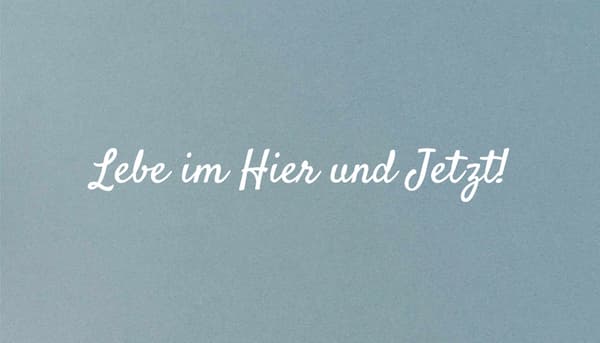
"Satisfy" ist eine beliebte Handschrift-Schriftart, die Eleganz mit einer persönlichen Note verbindet. Dank ihrer gut lesbaren Buchstaben eignet sie sich perfekt für Einladungen, Grüße und kreative Designs.
2. Petit Formal Script
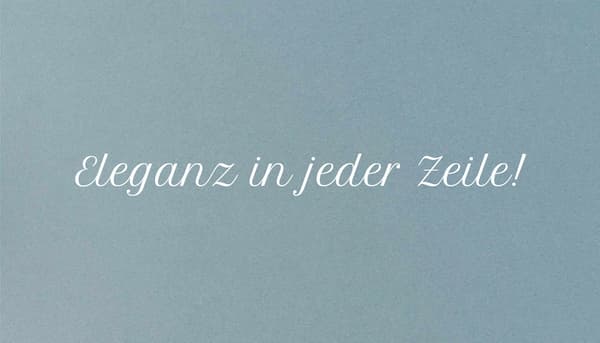
"Petit Formal Script" vereint die Eleganz handschriftlicher Linien mit einer klaren, strukturierten Ästhetik. Diese Schriftart ist ideal für klassische Einladungen, luxuriöses Branding und edle Verpackungsdesigns.
3. Just Another Hand
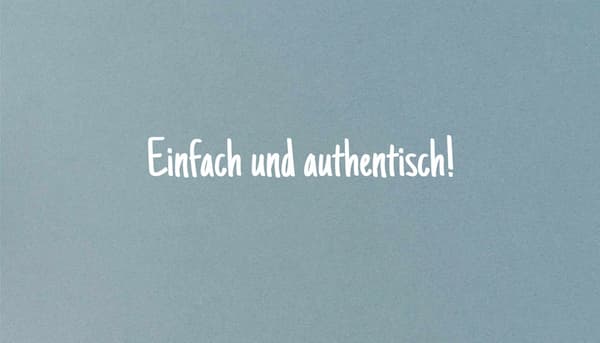
"Just Another Hand" ist eine schmale, mit dem Pinsel gezeichnete Handschrift, die von der Handschrift des Erstellers aus seiner Highschool-Zeit inspiriert wurde. Diese Schriftart wird häufig für Grußkarten, persönliche Briefe und Einladungen verwendet.
4. Nothing You Could Do
"Nothing You Could Do" ist eine natürliche, verspielte Schrift mit einem leicht schrägen Look. Ihre Schönheit liegt in ihrer Unvollkommenheit und Spontaneität. Sie eignet sich besonders für Designs, die Persönlichkeit und Individualität ausstrahlen.
5. Patrick Hand SC
"Patrick Hand SC" ist eine klare, gut lesbare Handschrift-Schriftart in Großbuchstaben. Sie eignet sich ideal für freundliche Anzeigen und Kinderbücher.
6. Oooh Baby
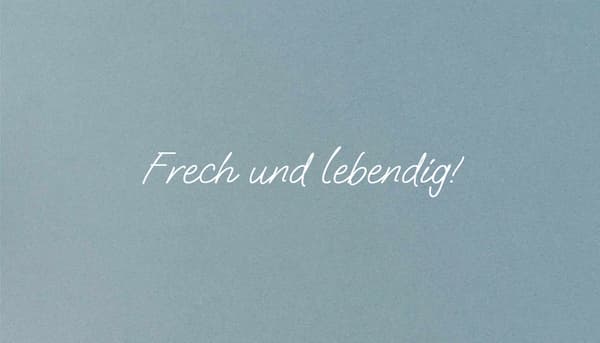
"Oooh Baby" ist eine fröhliche, verspielte Handschrift-Schriftart, die Designs eine lebendige und persönliche Note verleiht. Sie ist hervorragend für Einladungskarten, Produktverpackungen und ungezwungene Designs.
7. Just Me Again Down Here
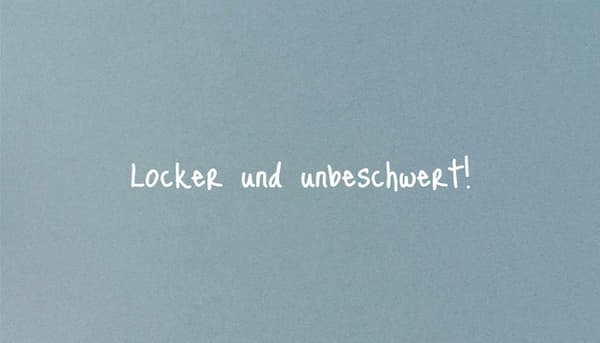
"Just Me Again Down Here" ist eine süße, leicht unordentliche Handschrift-Schriftart mit charmantem Charakter. Sie eignet sich ideal für freundliche Erinnerungen, persönliche Briefe und kreative Anzeigen.
8. Trade Winds
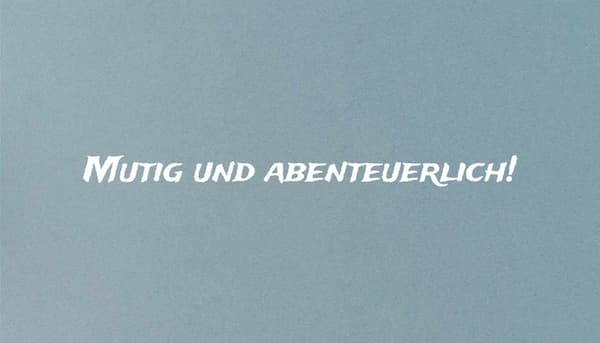
"Trade Winds" ist eine markante Handschrift-Schriftart in Großbuchstaben, die ein Gefühl von Abenteuer und Bewegung vermittelt. Sie eignet sich ideal für Branding, Reiseprojekte und sportliche Designs.
9. Haedus
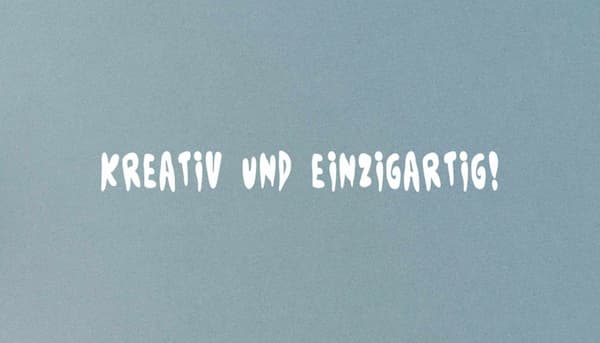
"Haedus" zeichnet sich durch eine kühne, handgemalte Ästhetik aus und verleiht Designs eine düstere, gruselige Atmosphäre. Diese Schriftart eignet sich perfekt für Halloween-Themen und Horror-Designs.
10. Caveat
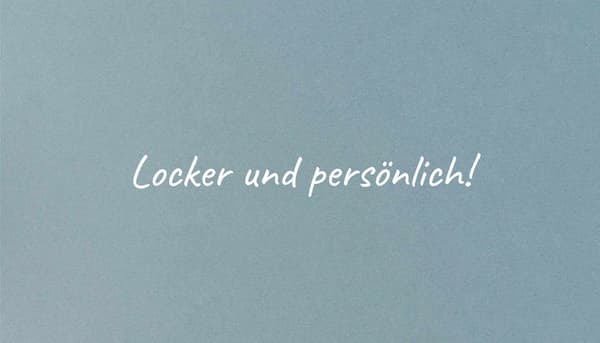
"Caveat" ist eine natürliche Handschrift-Schriftart mit einer verspielten und persönlichen Note. Sie verleiht Notizen, kreativen Designs und freundlichen Einladungen einen charmanten, handgeschriebenen Touch.
Es gibt viele digitale Schriftarten, die das Aussehen von Handschrift nachahmen. Beliebte Beispiele sind "Satisfy", "Caveat", "Patrick Hand SC" und "Just Another Hand". Diese Schriftarten wirken natürlich und eignen sich gut für kreative Designs, Notizen oder persönliche Einladungen. In der App PhotoDirector kannst du über 130 Handschrift-Schriftarten direkt auswählen und anpassen.
Eine gut lesbare Handschrift-Schriftart zeichnet sich durch klare Buchstabenformen und eine ausgewogene Linienführung aus. In der PhotoDirector-App kannst du viele Handschrift-Schriftarten direkt ausprobieren und individuell anpassen.